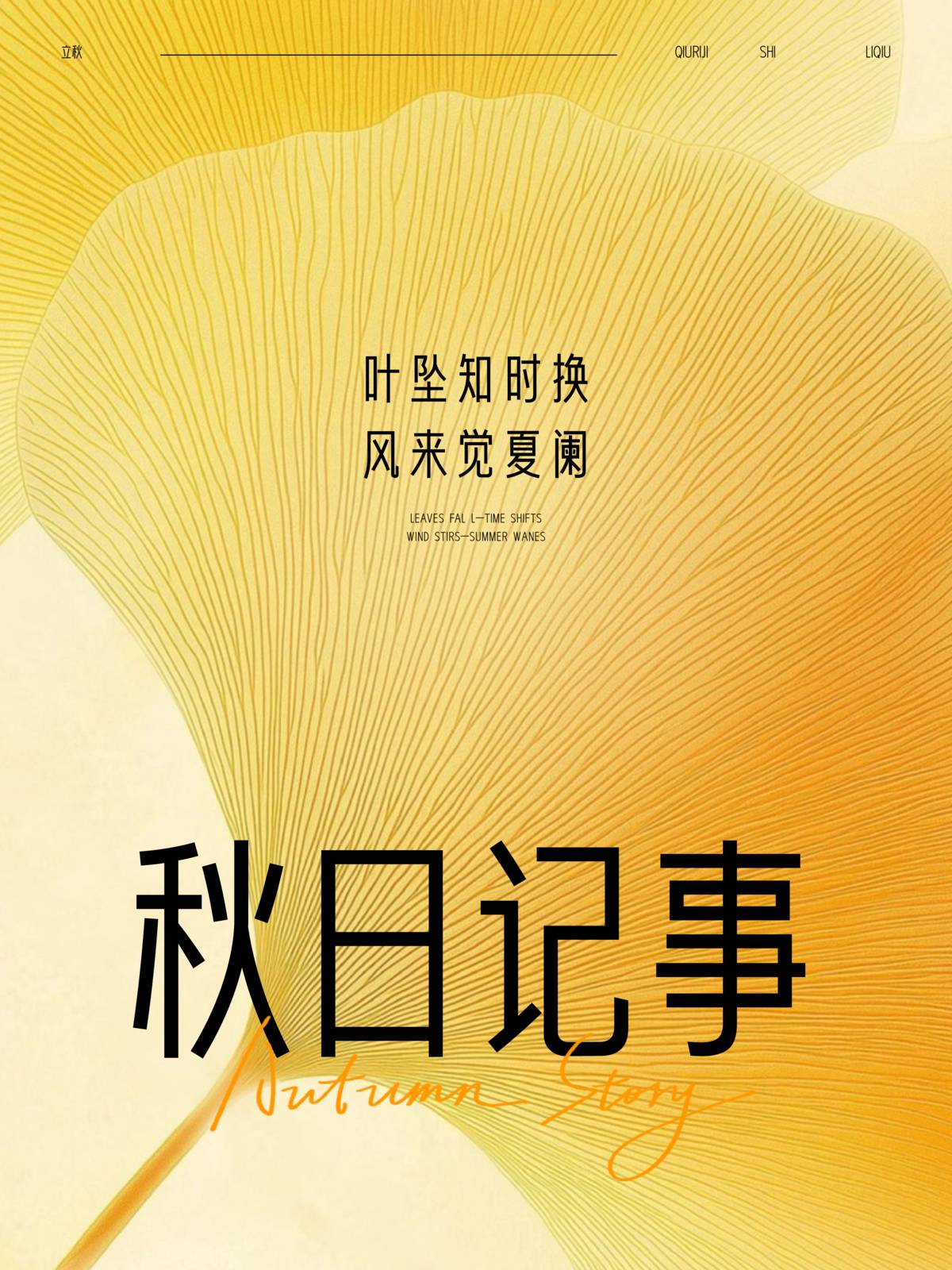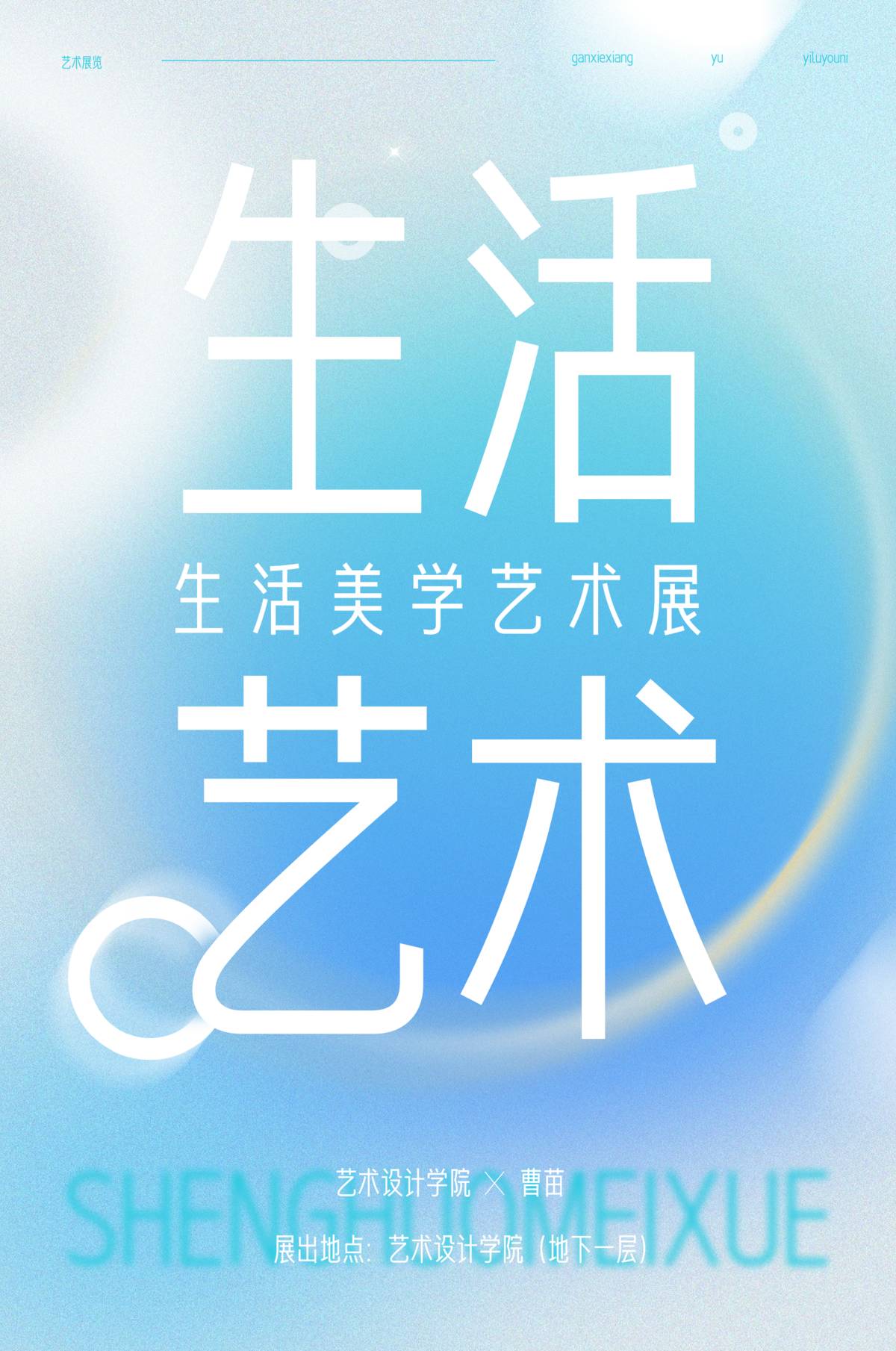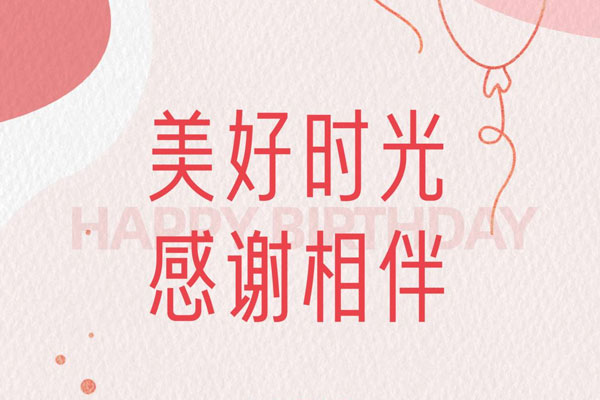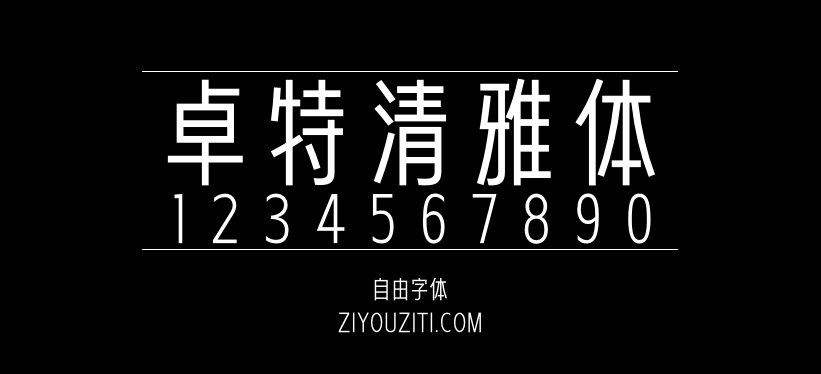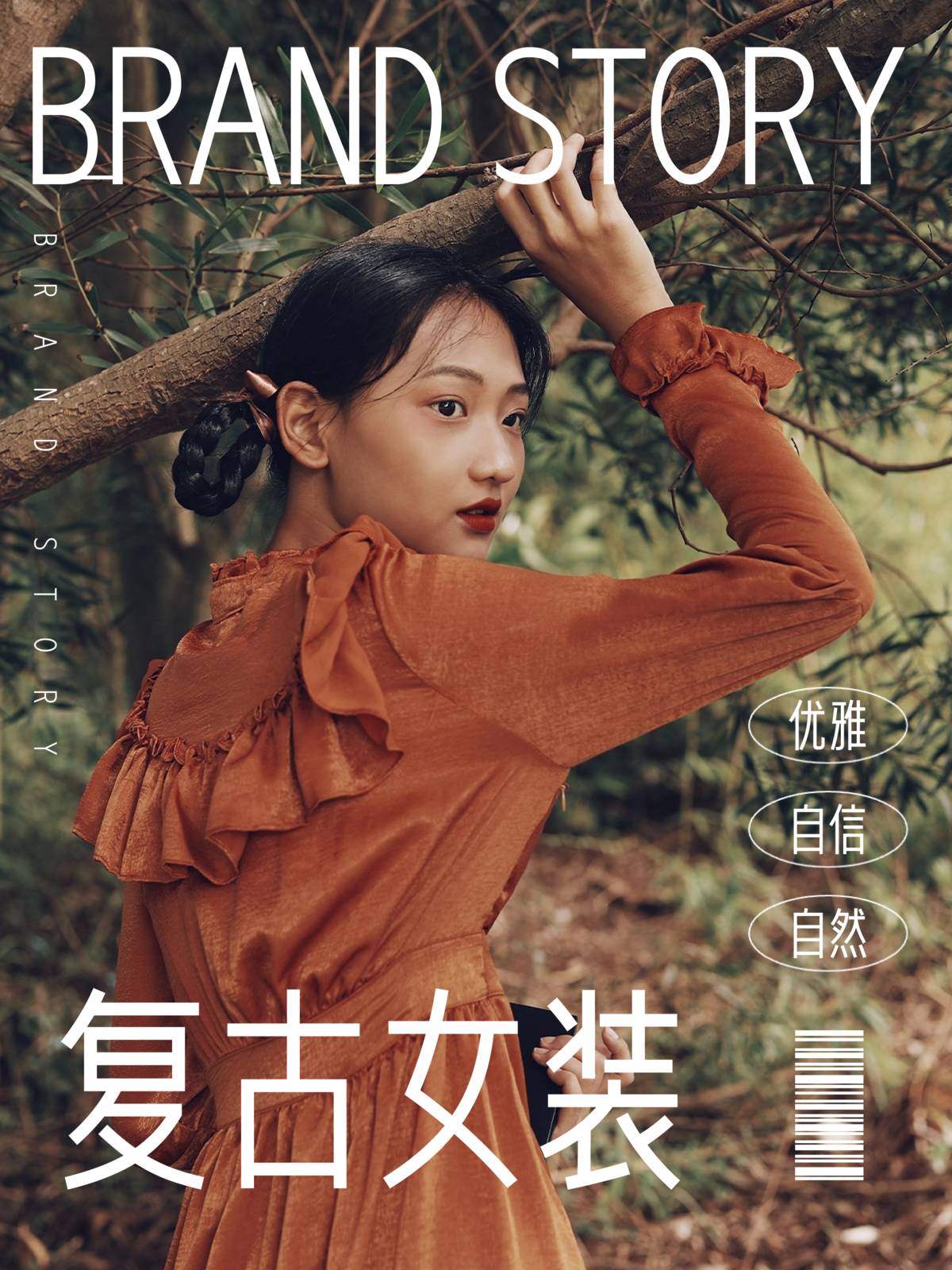
卓特清雅体
卓特清雅体(ZT QingYaTi)是国内领先的正版创意素材库与在线AIGC工具平台卓特视觉,与国内知名字体设计师、字体帮创始人刘兵克深度合作发布的高质量免费商用字体。
卓特清雅体字形瘦长挺拔,线条细致干净,具有强烈的现代化气息与技术审美。字面适度均衡,结构稳定,适合各类专业场景使用。经自由字体检测,目前卓特清雅体已覆盖GB2312规范的6763字,日常使用不会遇到缺字情况。
本字体包含 GB2312-80 标准中的 6763 个简体汉字及 420 个常用字符,共收录 7183 个字符,可满足日常办公、设计创作、品牌宣传等多元场景的字体使用需求。